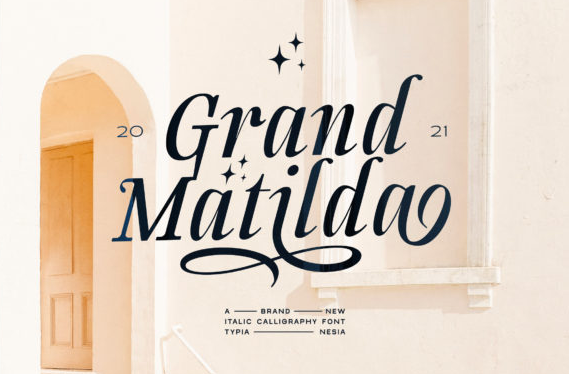
[Creativefabrica] Grand Matilda Font (2021)
Creativefabrica Grand Matilda Font (2021)
Grand Matilda - это красивый и изысканный шрифт.
Он имеет стильный, элегантный и современный вид, который можно использовать для всех ваших проектов. Grand Matilda закодирован PUA, что означает, что вы можете легко получить доступ ко всем глифам и штрихам!